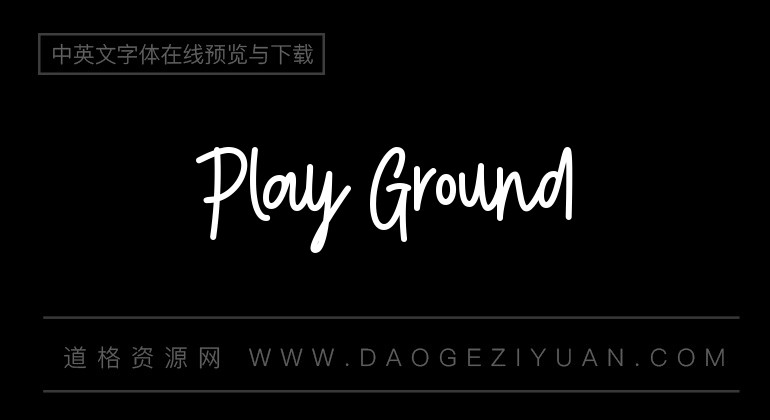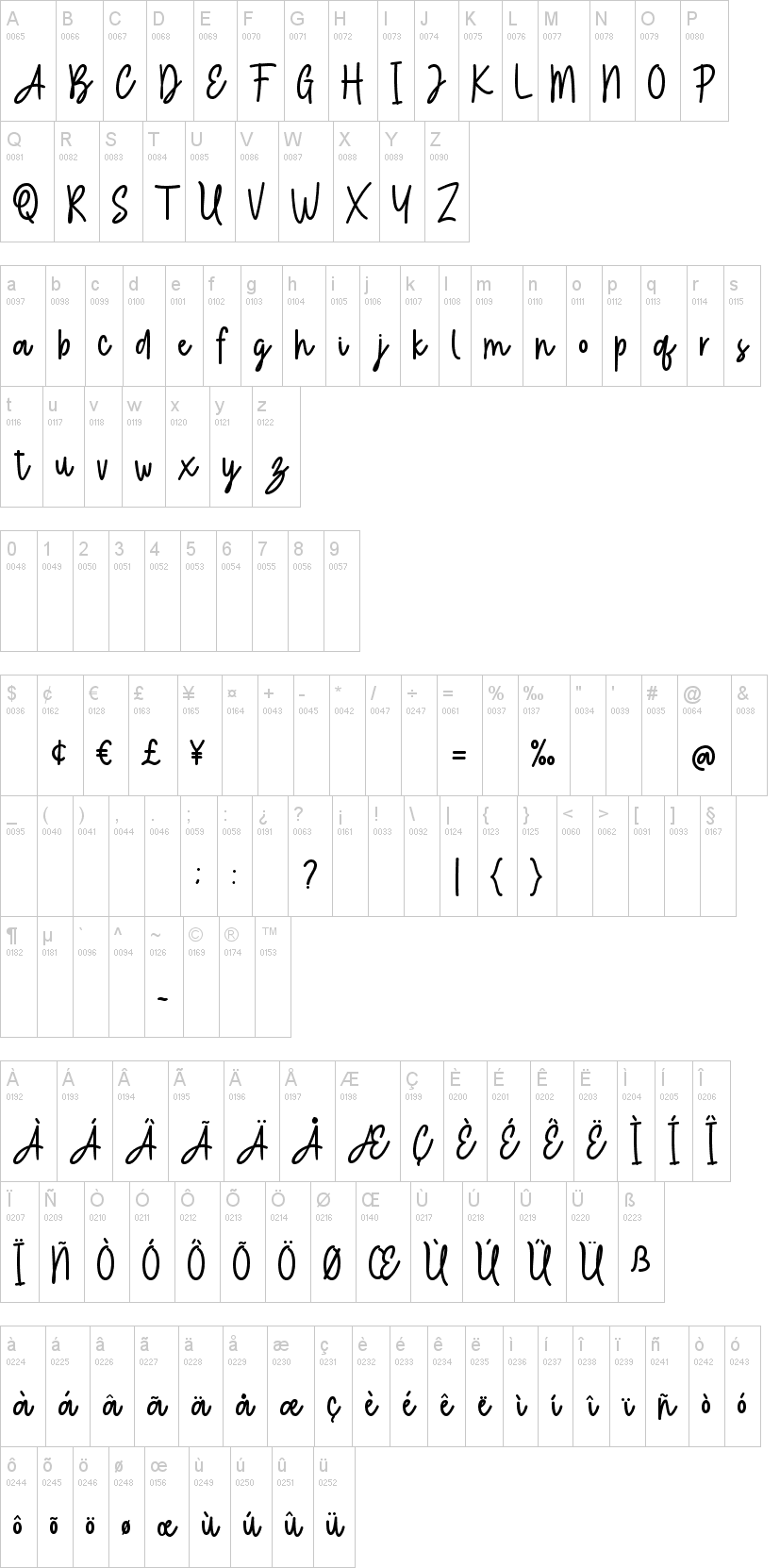
Play Ground 字体是一款非常精致的新型字体,它具有轻巧的外观,细节丰富,更易于阅读,适合各种设计项目,比如网页设计、印刷品设计、图标设计等。它具有简洁的字形,并且具有良好的可读性,可以提高文本的可视性,让文本更加简洁明了。此外,它还具有多种字重,可以根据不同的设计需求来调整字重,以满足不同的设计要求。内容介绍
Play Ground是一款非常不错的手写艺术字体,具有很好的视觉感,适合于文化类的宣传设计、商业类品牌的广告和产品包装设计以及个性化文字排版等较多场景。